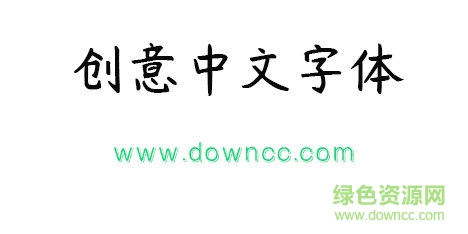
創(chuàng)意(創(chuàng)藝)中文字體是小編為大家整理的一系列創(chuàng)藝字體,該系列字體廣泛的應(yīng)用于各個(gè)行業(yè),如平面設(shè)計(jì)、廣告設(shè)計(jì)、美工等,可一鍵導(dǎo)入ps編輯器中,適合大部分辦公的人員使用,需要的朋友歡迎來綠色資源網(wǎng)下載!
1.字體結(jié)構(gòu)合理,筆劃前后統(tǒng)一。
2.筆形剛健有力,個(gè)性豪放,視覺沖擊力強(qiáng)。
3.適用于布置櫥窗、裝潢商品、制作廣告、設(shè)計(jì)書刊等。